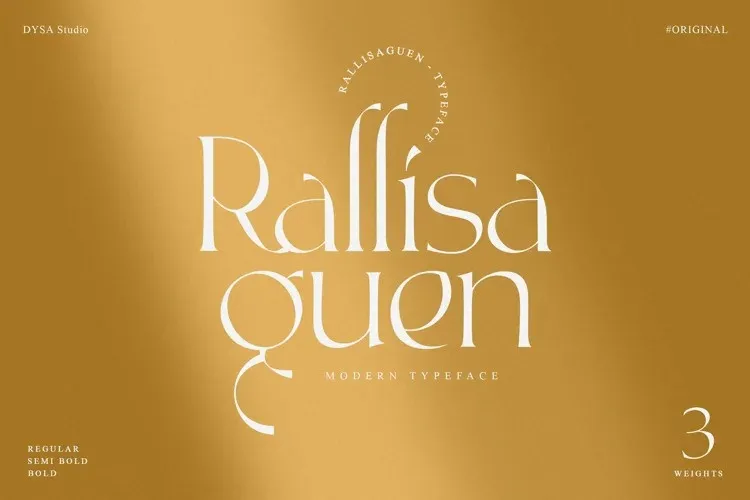
Rallisaguen Font – Fonte Grátis
Rallisaguen Font
Esta fonte serif foi criada pela DYSA Studio com um design que destaca claramente as nuances do estilo, oferecendo uma textura rica e arredondada. Com um contraste de letras acentuado, Rallisaguen se destaca em qualquer projeto editorial ou branding. Suas bordas levemente suaves conferem ao texto um aspecto autêntico de arte manual, tornando-a perfeita para incorporar na identidade visual de seu negócio. Seja para marcas, apresentações de slides ou até mesmo designs gráficos complexos, Rallisaguen proporciona o tom certo para qualquer projeto que precise de uma aparência elegante e sofisticada, reforçando a personalidade única do seu empreendimento.